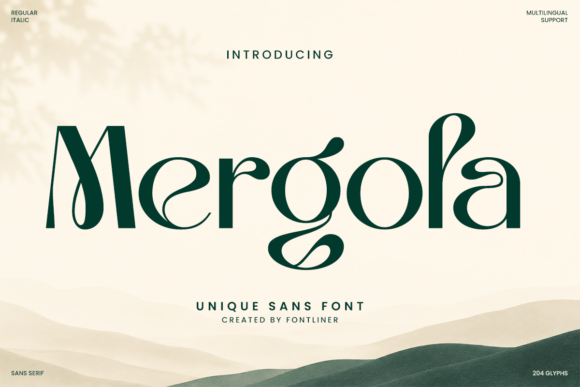
Mergola
適切なデザイン要素を見つけるのは難しい場合がありますが、Mergolaは作品を即座に引き立てる優れたコレクションを提供します。
精密に作られたMergolaは、クリーンなベクター、滑らかなタイポグラフィ、そして安心のための商用ライセンスを提供します。
POD(オンデマンド印刷)製品、結婚式の招待状、またはソーシャルメディアのグラフィックを作成している場合でも、Mergolaは理想的です。